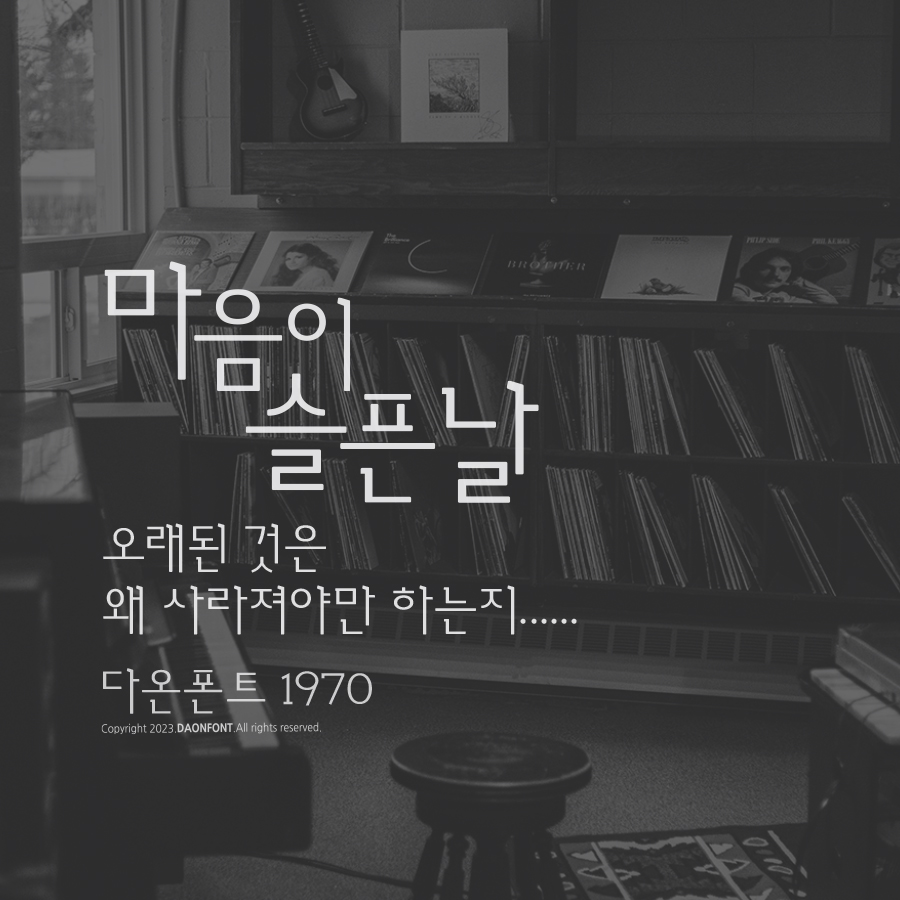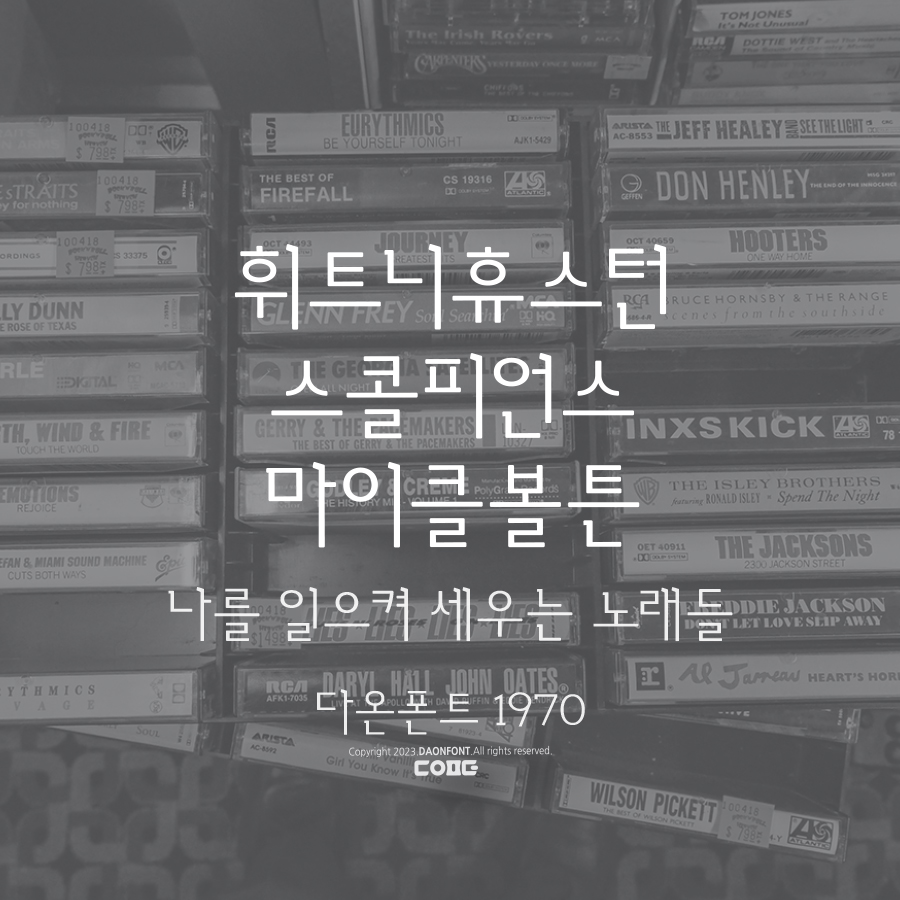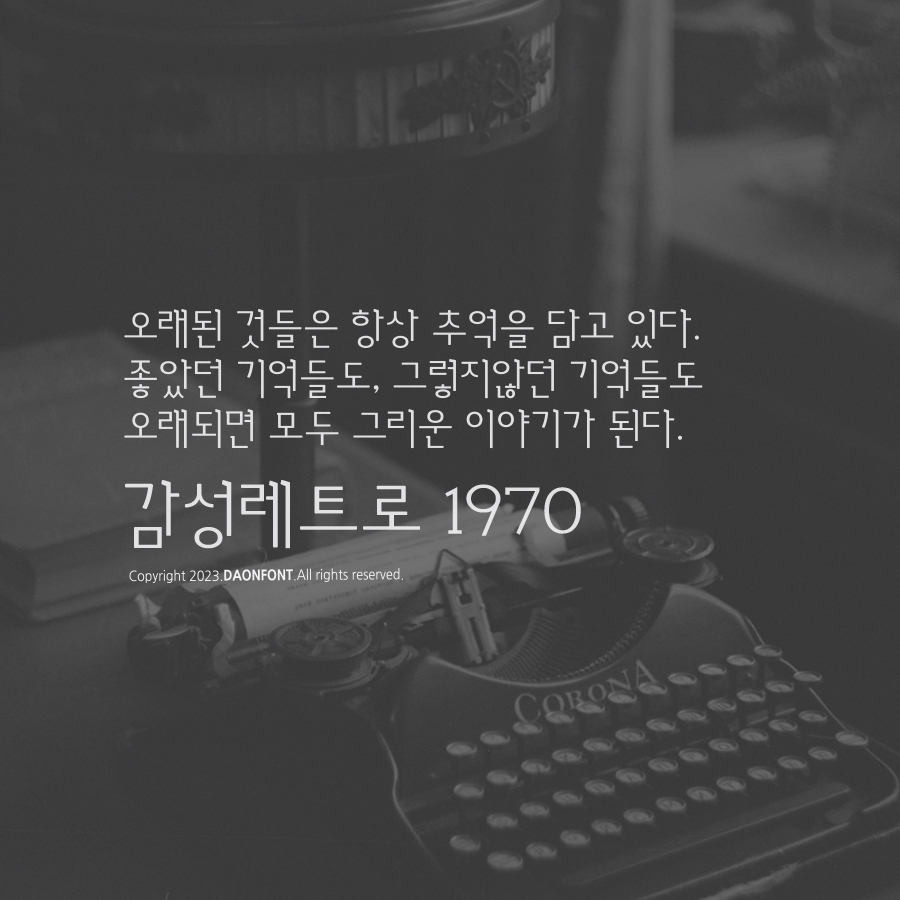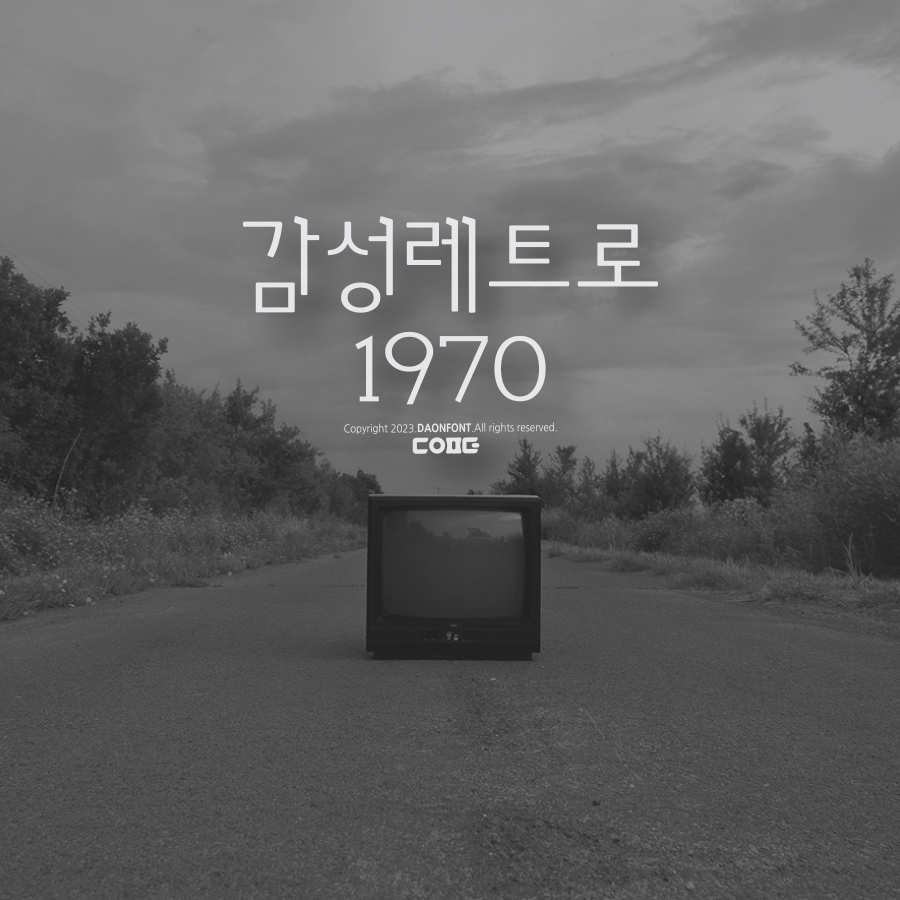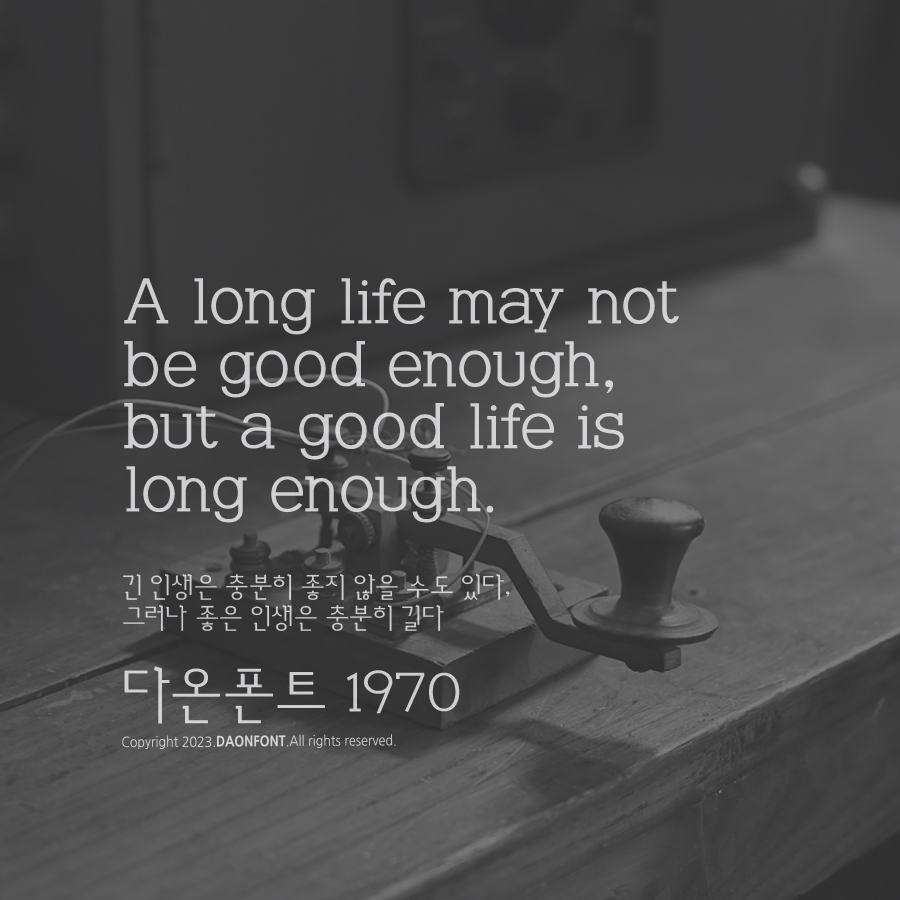
3월 두번째 신서체 다온폰트 '일구칠공' 출시
3월 두번째 신서체인 다온폰트 "일구칠공"이 업데이트 되었습니다.
다온폰트 "일구칠공"은 카피용 서체로 한글 2,780자, 영어 대/소문자, 숫자0~9, 특수문자, 딩벳으로 구성되었고
굵기에 따라 2종(Light / Medium)으로 사용하실 수 있습니다.
레트로 감성으로 타자기가 연상되는 서체로 여러 용도에 다양하게 사용하실 수 있습니다.